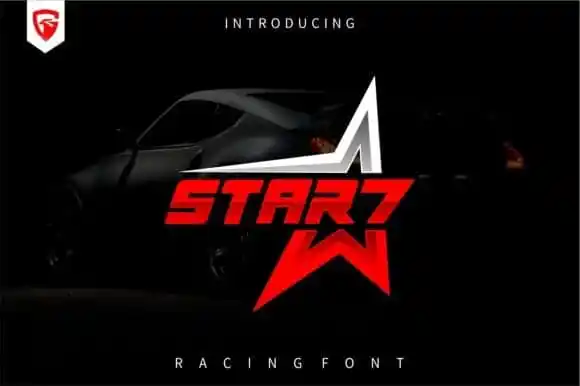
Star7 Display Font
Star7 Display Font é uma elegante e moderna tipografia para uso em destaque que oferece um toque luxuoso com suas linhas robustas. Desenhada por GFRcreative, essa fonte perfeita para diversos projetos: desde logomarcas e identidades visuais até posts de blog e cartazes publicitários. Suas linhas agudas e elegantes são ideais para destacar seus eventos esportivos ou qualquer projeto que deseje um toque moderno e sofisticado. Adicione Star7 a seu próximo evento esportivo e veja como ela faz uma grande diferença, transformando-o em destaque. Suas linhas fortes se encaixam perfeitamente no estilo de diferentes formatos e aplicações, permitindo que você personalize sua marca ou conteúdo de maneiras criativas e eficazes. Aqui está uma fonte pronta para usar, simplesmente esperando ser adicionada ao seu próximo projeto visual.